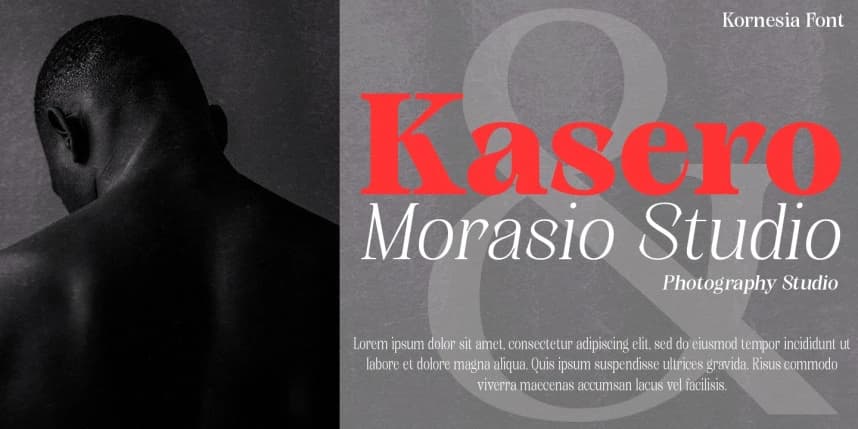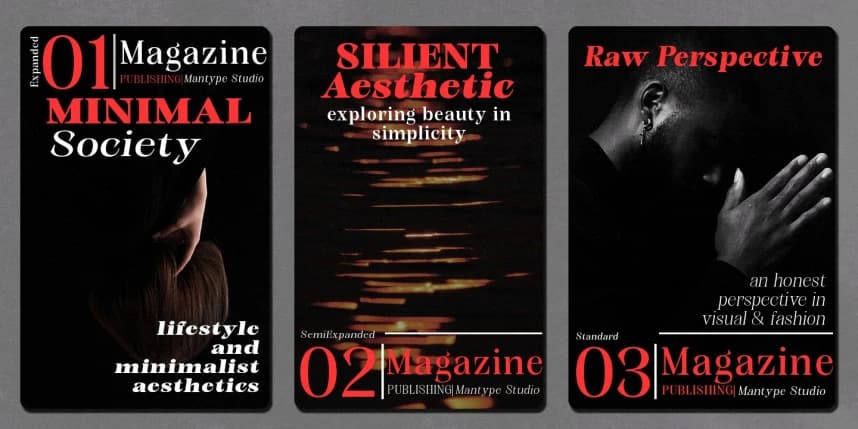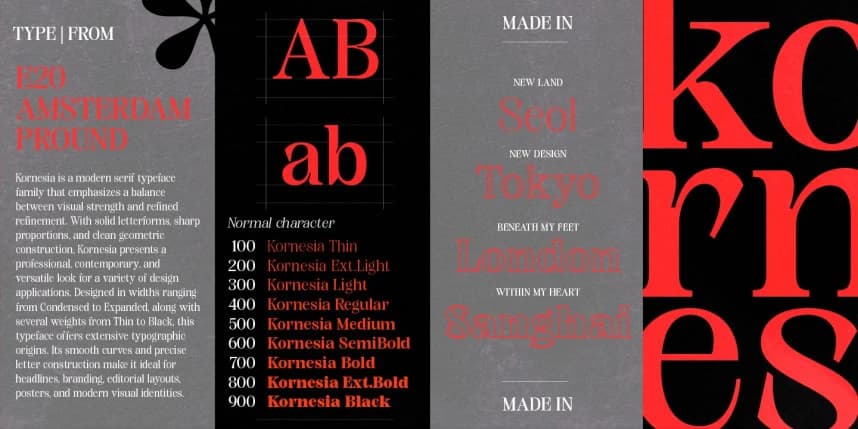
Kornesia Contrast Font, kalın ve ince çizgiler arasındaki yüksek kontrastla lüks bir serif yazı tipidir ve zarif, modern ve premium bir his verir. Dengeli oranlar ve rafine ayrıntılarla tasarlanan bu yazı tipi, başlıklarda öne çıkar ve okunabilirliğini korur.
Kornesia Contrast Font, kalın ve ince çizgiler arasında yüksek kontrasta sahip lüks bir serif fontudur ve zarif, modern ve premium bir his verir. Dengeli oranlar ve incelikli detaylarla tasarlandı; başlıklarda öne çıkar ve okunabilirliğini korur.